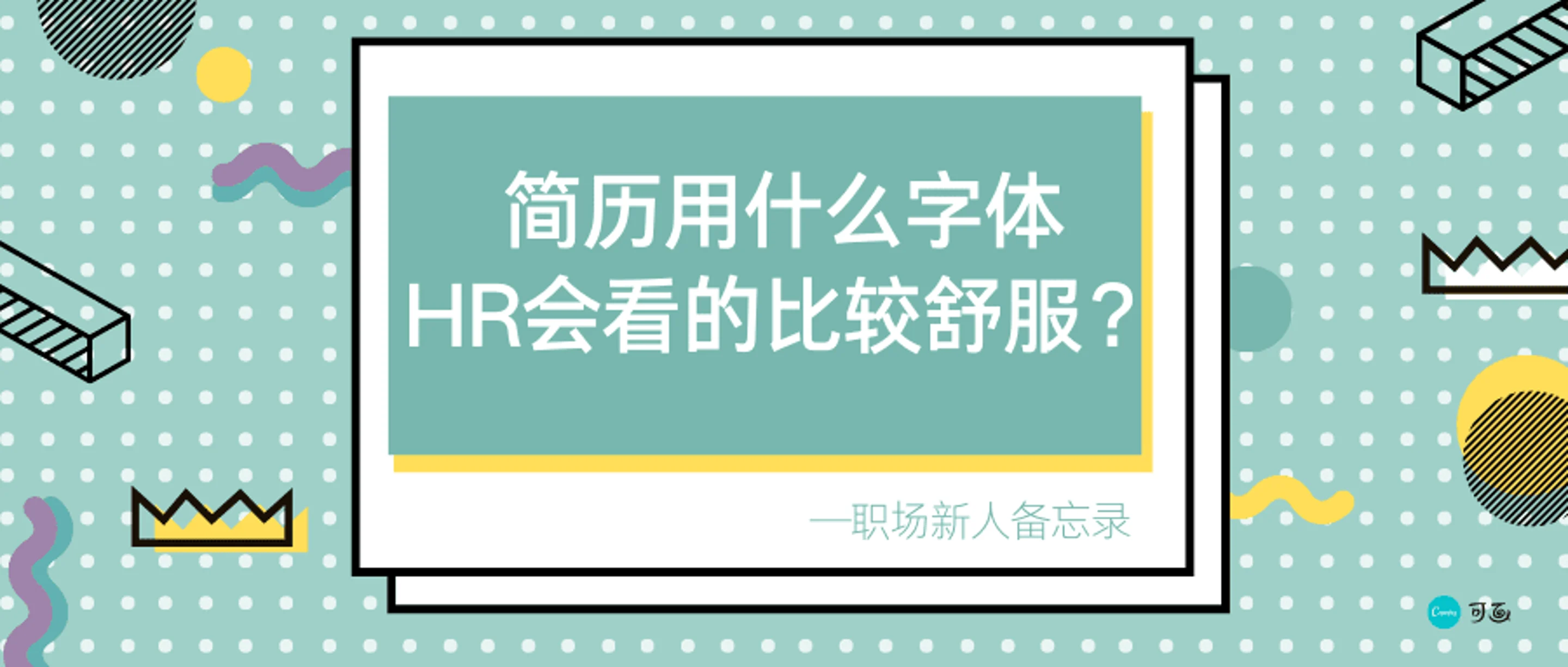
正所谓见字如面,简历采用什么字体,早已成为影响简历(在新标签页或窗口中打开)视觉反馈的直接因素。
这里我们先要给大家说一个误区
除开纯艺术岗位,所有选择自己手写简历然后转成电子格式的简历文件,都是在挑战HR的底线。
简历的视觉美观虽然重要,但归根结底信息传递,才是简历设计的核心。
采用各种花里胡哨的字体或手写简历,都会主动降低HR筛选简历的效率!
回到正题,简历采用什么字体,建议大家从3个方面进行筛选。
一份简历当中的中文或英文字体,尽量不要出现超过两种。
通常是标题一种字体、正文一种字体即可。
简历中出现过多的字体设计,会导致版面的文本层级失衡,最终造成HR浏览简历时阅读更加困难。
简历的字体颜色大家老老实实的选择黑色即可,别想用什么别的字体颜色,去挑战HR的工作耐心。
斜体则是不推荐大家在简历中使用,一方面斜体是西文字体样式,本身就不是十分适用于中文语境。
另一方面,斜体在中文语境中更多的表示引用。但简历文本中,极少会出现“引用”的表述形式,盲目使用斜体字体会显得十分奇怪。
黑体加粗是突显简历关键词的一个小技巧。但需要注意的是,整个简历的加粗词汇尽量不要超过3个,否则就变成了“全文强调”,从而丧失了原有的提示效果。
关于简历采用什么字体和需要注意的字体样式,以上就是我们给大家分享的主要内容。